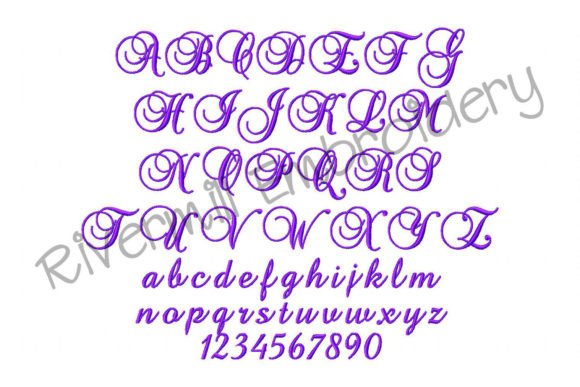
Requited Script Embroidery Font
Requited Script Embroidery Font — це елегантний, ручно створений шрифт у форматі PES, спеціально розроблений для машинної вишивки у стилі каліграфічного рукопису. Його плавні лінії, добре продумані з’єднання літер та природна асиметрія надають вишивці живої, людської енергії, що різко відрізняє його від типових механічних скрипт-шрифтів. Цей шрифт ідеально підходить для вишивки імен, цитат, весільних прикрас та особистих подарунків, де важлива не лише читабельність, а й емоційна глибина.
Як це порівнюється з конкурентами
На відміну від популярних безкоштовних PES-скриптів (напр., ‘Lavender Script’ або ‘Sweet Pea’), Requited має значно вищу роздільну здатність стібків, більш природну каліграфічну динаміку та професійну оптимізацію під реальні умови вишивки. Порівняно з преміальними альтернативами (напр., ‘Scribble Script’ від Embroidery Library), Requited відрізняється меншою жорсткістю контурів і кращою адаптацією до криволінійних поверхонь (напр., рукавів або сумок), хоча й має менший набір варіацій стилів (немає жирного або курсивного варіантів).